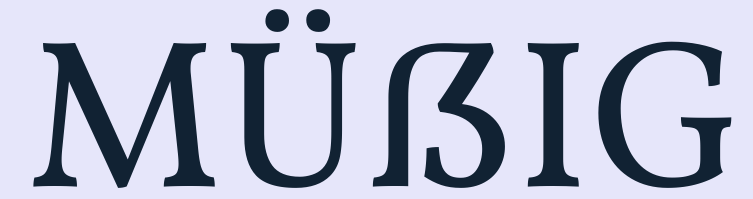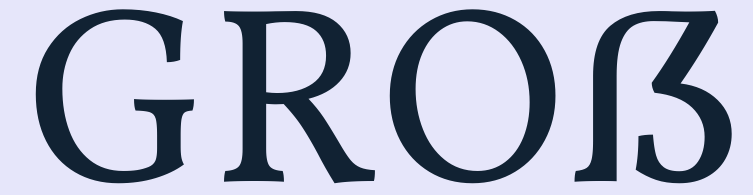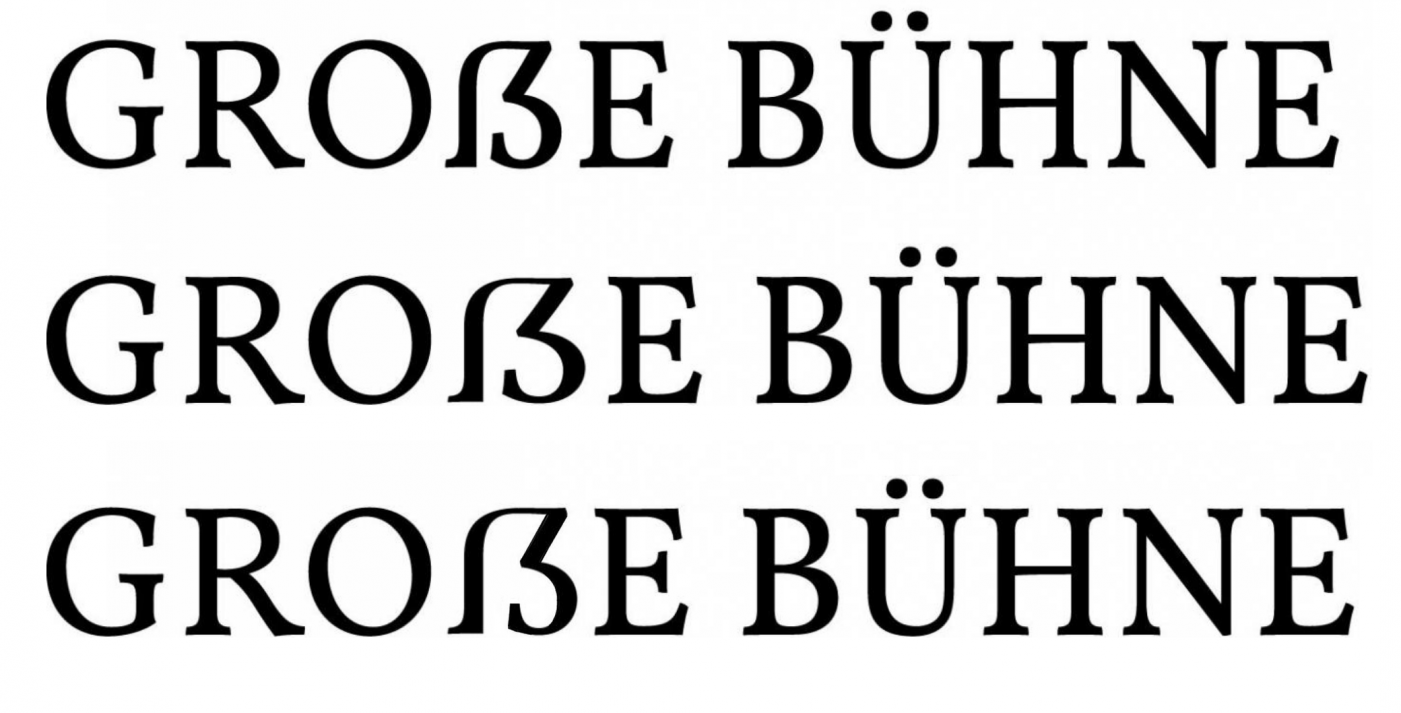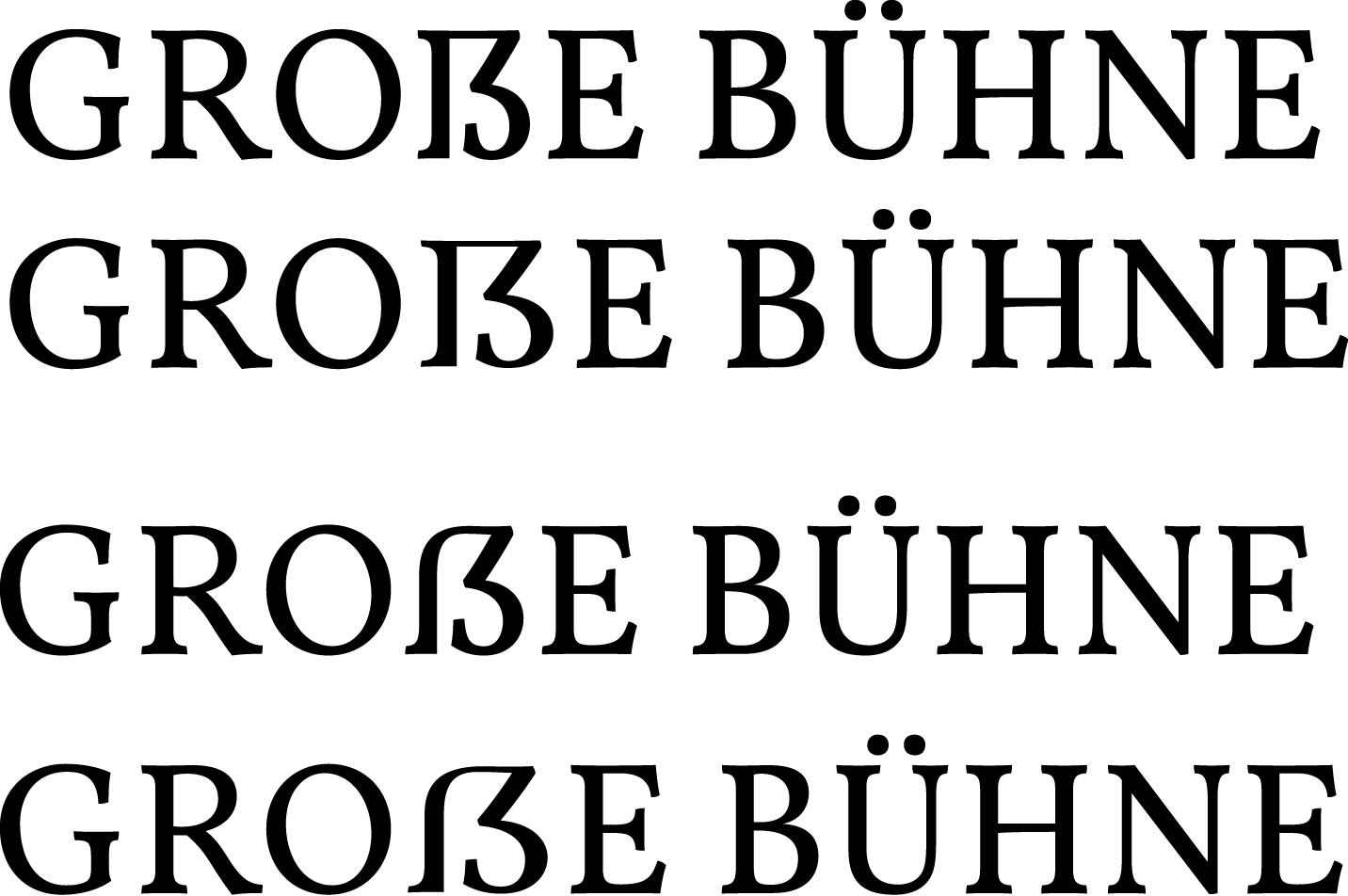
Das große Eszett beim gemeinen Anwender:
In meiner freien Zeit bin ich bei einem kleinen Theater aktiv. Neben dem Spielen kümmere ich mich so um dies und das, u.a. setze ich die Texte neu (die Versionen, die von den Verlagen kommen, sind, was die Übersicht und Lesbarkeit betrifft, eher suboptimal).
Auf jeder Titelseite steht oben (über dem Titel des Stückes) in der zweiten Zeile »GROẞE BÜHNE«, gesetzt in der Vollkorn 24 pt. Ich habe den (mit Word 2010) fertig formatierten Text (+ den verwendeten Schriften) meinem Freund und Regisseur geschickt. Dieser meldete sich, dass das große Eszett zwar bei ihm auf dem Bildschirm zu sehen sei, es aber beim Ausdruck verschwände (er nutzt Office 365). Irgendetwas ist das schiefgegangen - ich schrieb ihm er solle doch einfach das große Eszett noch einmal mit Alt+7838  einfügen . Und jetzt komme ich zum Kern dieser etwas länglichen Vorrede. Er schrieb mir per Mail: »Super, hat mit dem Shortcut geklappt! Musste beim großen Eszett dann aber noch die Schriftgröße von 24 auf 26 Punkt erhöhen, damit es auch größenmäßig passte.«
Diese Reaktion kann ich sehr gut nachvollziehen. Ich habe bei vielen Varianten des großen Eszett ebenfalls den Eindruck, dass es »größenmäßig« nicht passt. Es fehlt m.E. häufig das »großbuchstabige«, viele Eszett erscheinen zu klein, zu niedrig (das sieht aber nur so aus), zu schmal etc. Ich habe mal auf die Schnelle mal was mit der Vollkorn gebastelt (sie bietet ja zwei Varianten des großen Eszett).
Erste Zeile das Original, in der zweiten Zeile habe ich das große Eszett skaliert auf 120% und noch eine weiße Kontur gelegt, um die Strichstärke einigermaßen zu halten (Wie gesagt schnell und schmutzig). In der jeweils zweiten Zeile erreicht das Eszett jetzt die Breite des »O«. Ich empfinde die breite Variante als wesentlich stimmiger - sie passt sich besser in das »Großbuchstabenbild« ein.
Was haltet Ihr davon?
GROTZE BÜHNE!! Hach, ich kann mich mit der harten Ecke links oben einfach nicht anfreunden.
Ich bin einverstanden, dass eine Dehnung nötig ist. Bei der letzten Version hast Du's aber vielleicht etwas übertrieben. Ich würde stattdessen raten, das Innenleben etwas nach rechts zu schieben, um das «Vertical Stacking» der Zürich-Form zu erreichen. 🤓
Außerdem ist die Glyphe tatsächlich etwas zu tief gezeichnet. Sie passt nicht aufs Dach des /E/ nebenan. Ich hab das auch noch etwas aufskaliert.
Tja, das ist halt das Problem bei Schriften mit solch klassischen Buchstabenproportionen. Soll sich das ẞ da am ausladenden O orientieren oder eher am schmalen E? Da wir da auf keine Sehgewohnheiten zurückgreifen können, die uns »natürlich« erscheinen, gibt es da vielleicht keine allgemeingültige Lösung. Vielleicht wären ja Alternativformen, schmaler und breiter, je nachdem, wo das ẞ steht, sinnvoll?
Vielleicht wären ja Alternativformen, schmaler und breiter, je nachdem, wo das ẞ steht, sinnvoll?
Ach was! Das tut man ja für andere Buchstaben auch nicht. Beim Eszett find ich aber tendenziell breit besser.
vor 3 Minuten schrieb CatharsisFonts:
Das tut man ja für andere Buchstaben auch nicht.
Stimmt. Aber da haben wir uns halt auch schon ein eine Standardproportion gewöhnt. Aber beim ẞ? Findest du wirklich, dass es (ich habe oben noch mal Beispiele verlinkt) in MÜẞIG zu schmal aussieht? Neben dem O ist das dann vielleicht anders. What do? :-?
Von den Proportionen her betrachtet gehört das ẞ in der gleichen Gruppe wie beispielsweise B und R. Von daher ist das ẞ nicht zu breit. Dafür ist das U der Vollkorn recht schmal und im Vergleich zum B ist das R verdammt breit …
vor 1 Minute schrieb Albert-Jan Pool:
Von den Proportionen her betrachtet gehört das ẞ in der gleichen Gruppe wie beispielsweise B und R.
Das seh ich anders. Es muss mMn breiter sein, um richtig auszusehen.
vor 11 Minuten schrieb Þorsten:
Findest du wirklich, dass es (ich habe oben noch mal Beispiele verlinkt) in MÜẞIG zu schmal aussieht?
Wo?
Ich will ja nicht die Diskussion stören, aber da wir grad über über ẞ-Proportionen reden, zeige ich mal mein aktuelles Corona-Stubenarrest-Machwerk:
vor 29 Minuten schrieb CatharsisFonts:
Vielen Dank für die Detailkritik an den Vollkorn-Versalien!
Wenn ich mich recht entsinne, hatte ich beim Entwurf der Vollkorn vor allem den gemischten Satz im Blick. Gleichzeitig hatte ich offenbar die Möglichkeit von Versalsatz völlig vernachlässigt. Das würde zumindest alle diese Ungereimtheiten der Zeichenbreiten etwas erklären …
Irgendwann einmal wird es eine Überarbeitung geben, die all diesen Hinweisen Rechnung tragen wird. Ganz bestimmt!